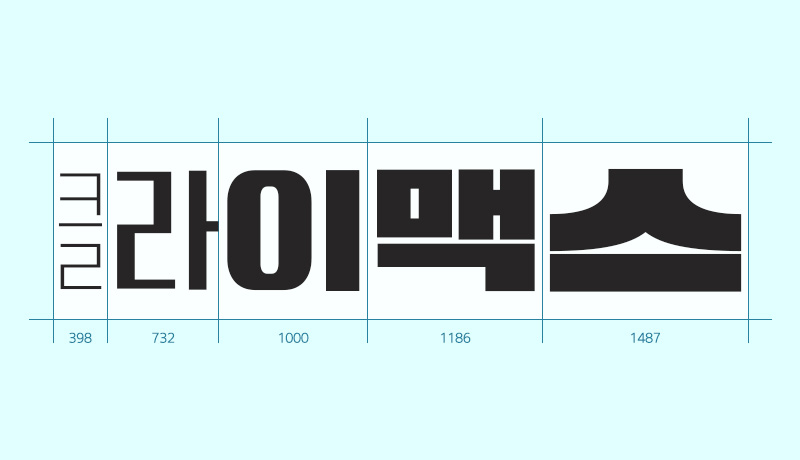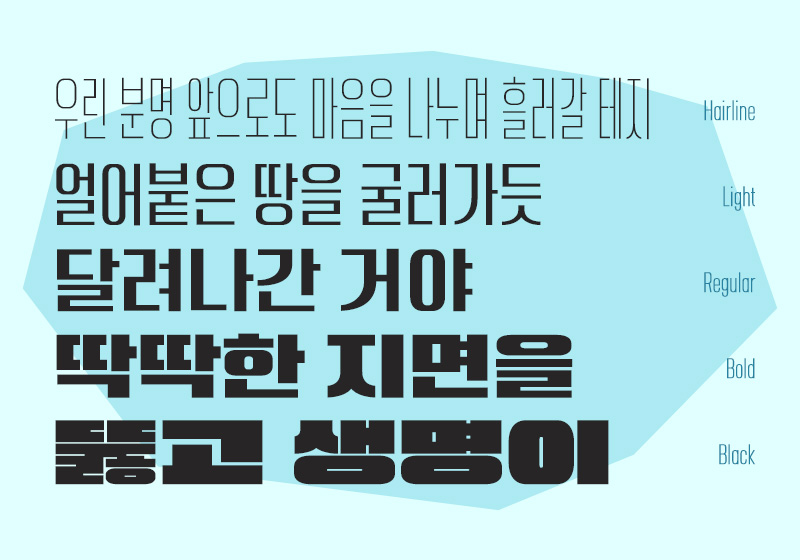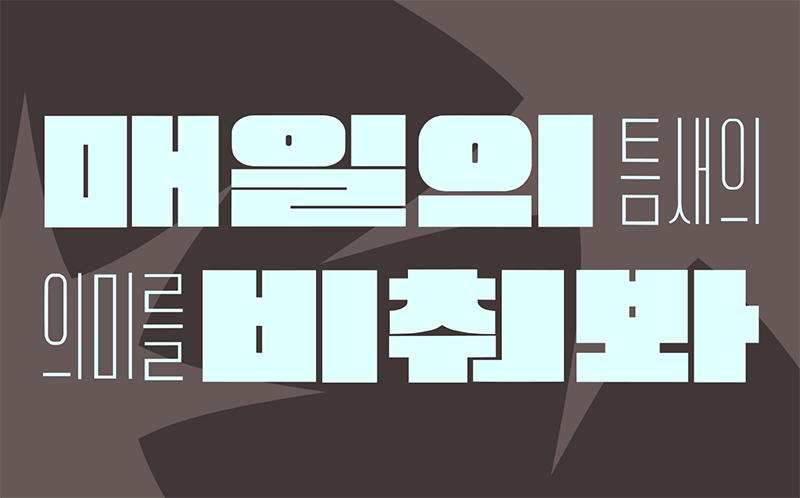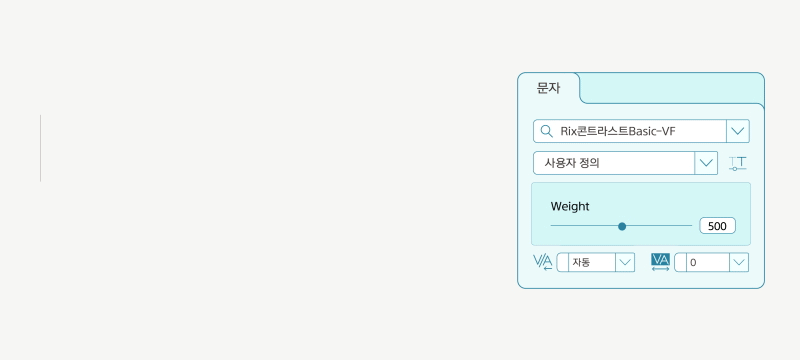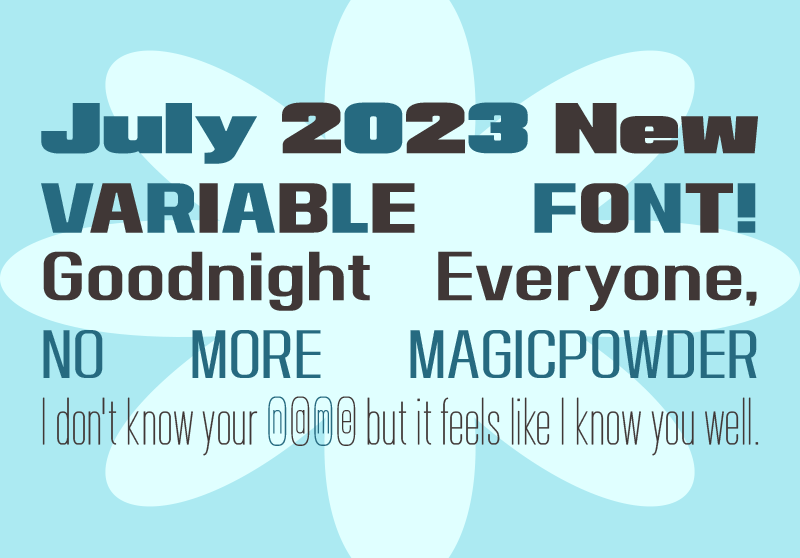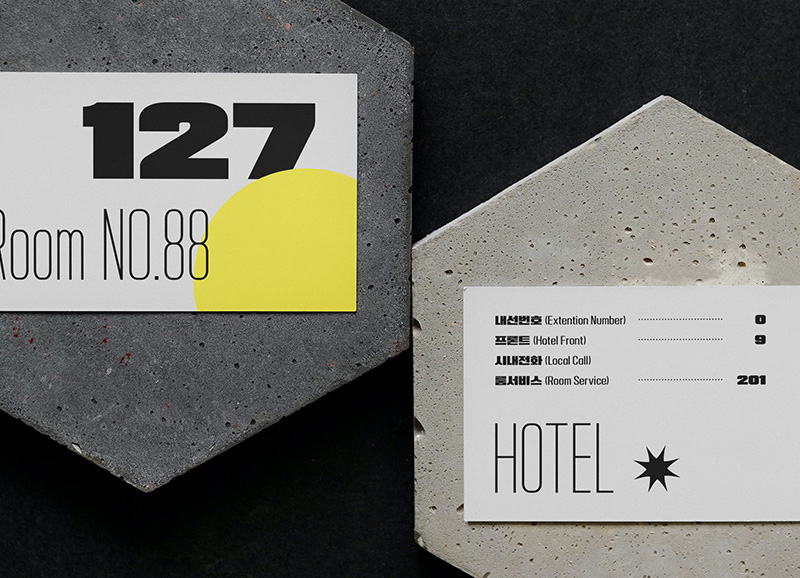
Rix콘트라스트 Basic VF
RixContrast-Basic-VF
2개의 시리즈로 구성된 Rix콘트라스트 배리어블 폰트의 베이직 버전입니다.
Basic-VF는 얇고 좁은 글자부터 두껍고 넓은 글자까지 Weight 축을 통해 굵기와 폭을 동시에 조절합니다.
강한 대비와 강렬한 인상은 극적인 효과를 주기에 좋고 배리어블 축으로 편리하게 사용할 수 있습니다.
| FontFamily | Rix콘트라스트-Basic-VF / RixContrast-Basic-VF |
| Design | Yun Yu-min, Yu Hyun-Ju |
| Direction | Park Yong-rak |